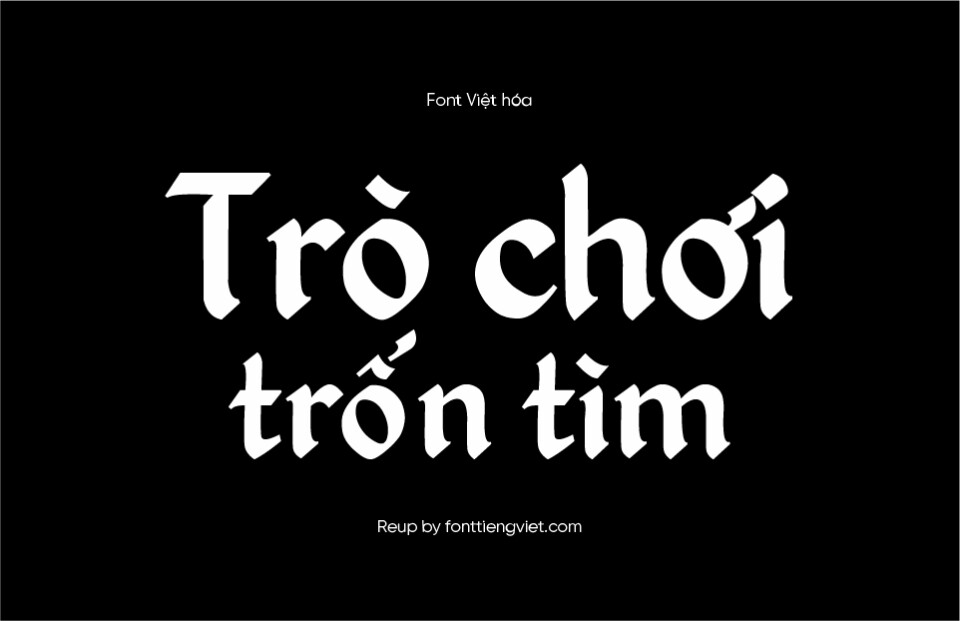
Font Việt hóa Kingthings Petrock Vi
Giới thiệu về Font Việt hóa Kingthings Petrock Vi
Nếu bạn đang tìm kiếm một bộ font mang phong cách cổ điển pha chút huyền bí cho các bài giảng hay dự án sáng tạo thì Font Việt hóa Kingthings Petrock Vi chính là sự lựa chọn tuyệt vời nhất. Đây là một mẫu thiết kế độc đáo từ nhà Kingthings, nay đã được tối ưu bảng mã tiếng Việt hoàn chỉnh. Việc sử dụng Font Miễn Phí giúp học sinh và giáo viên dễ dàng tiếp cận những phông chữ đẹp mà không lo ngại về vấn đề chi phí bản quyền.
Đặc điểm nổi bật của phông chữ
Bộ font này sở hữu những đường nét uốn lượn tinh tế, mô phỏng phong cách chữ viết tay thời trung cổ nhưng vẫn giữ được sự rõ ràng cần thiết. Các ký tự được điều chỉnh khoảng cách hợp lý, giúp văn bản không bị rối mắt khi trình bày trên các khổ giấy lớn hoặc slide bài giảng điện tử. Nhờ sự kết hợp giữa nét thanh và nét đậm, Kingthings Petrock tạo nên một cảm giác trang trọng và vô cùng nghệ thuật cho người xem.
Ứng dụng thực tế của Font Việt hóa Kingthings Petrock Vi
Sử dụng trong giáo dục và sáng tạo
Mẫu font này cực kỳ phù hợp để thiết kế tiêu đề cho các báo tường, thiệp mời sự kiện trường học hoặc bìa sách tiểu thuyết. Các em học sinh có thể dùng nó để trang trí các dự án cá nhân, giúp sản phẩm học tập trở nên sinh động và chuyên nghiệp hơn. Ngoài ra, phông chữ còn hoạt động tốt trên các phần mềm thiết kế phổ biến như Canva hay Photoshop, giúp quá trình sáng tạo trở nên mượt mà.